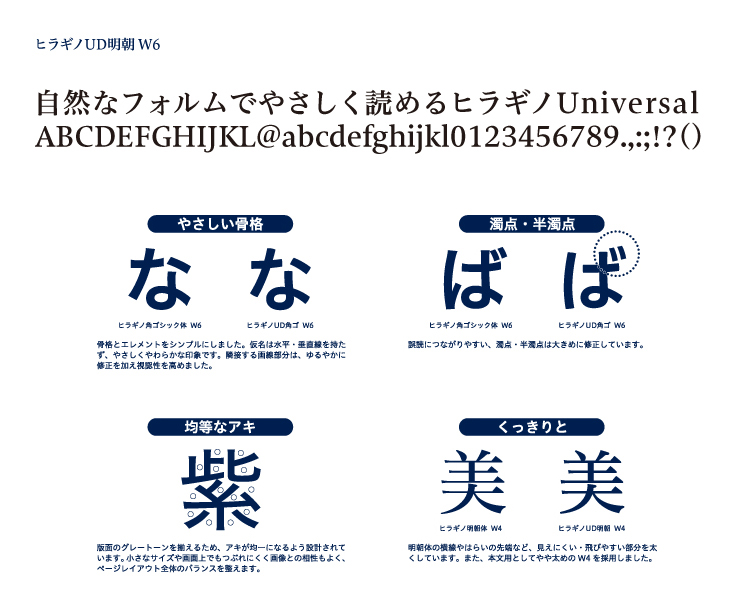
ヒラギノUD明朝 StdN W6|ヒラギノフォント|和文・欧文・デザイン書体のダウンロード販売|フォントファクトリー
【ヒラギノUD明朝】「ヒラギノ明朝」の基本デザインを受け継ぐユニバーサルデザインのフォントです。長い文章の読みやすさを求めて、字面をやや小さめにまとめ、仮名には長く読んでも疲れない柔らかな骨格を採用。小さな文字での印刷や、組込みやディスプレイなどでも使いやすい明朝体をめざしました。